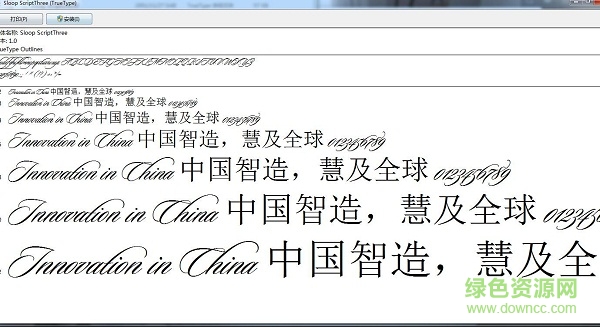
1.字體的外形經(jīng)長(zhǎng)期演變,已形成規(guī)范化的外形,或方、或圓、或三角,但伴隨著人類(lèi)文化發(fā)展到一定程度后,規(guī)范的字體外形顯得比較呆板,突破過(guò)于呆板的字體外形,必然成為現(xiàn)代眾多媒介中表現(xiàn)的主導(dǎo)方向之一。
2.無(wú)論漢字還是拉丁字體,在遵循字體總體外形規(guī)范的基礎(chǔ)上,可有所選擇地將其中一到兩個(gè)筆畫(huà)突破外形的界定,或向外延伸、相連,或收縮、與其它筆畫(huà)相依,其次還可根據(jù)具體表現(xiàn)主題的需要將字體變化成各種無(wú)機(jī)形態(tài)。